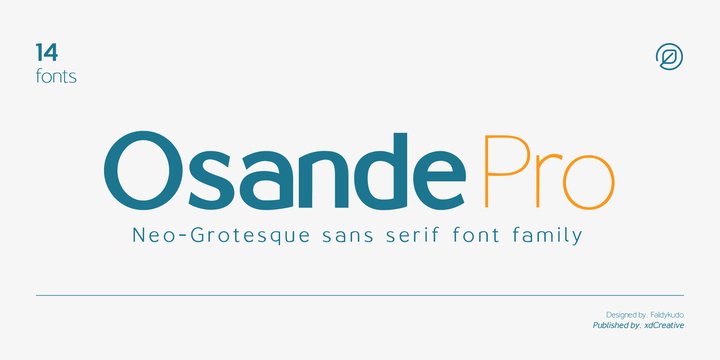
Myfonts Osande Font
[Myfonts] Osande Font
Osande - современный шрифт sans serif с неогротескным оттенком, более однородными формами с минимальным контрастом начертания.
Семейство шрифтов Osande содержит 3 основные формы: курсив, косые и вертикальные. Каждая из них имеет 7 различных начертаний (тонкое, сверхтонкое, светлое, обычное, среднее, полужирное и жирное).
Osande можно легко подобрать к невероятно большому набору проектов, поэтому добавьте его в свои творческие идеи и обратите внимание на то, как он их выделяет!